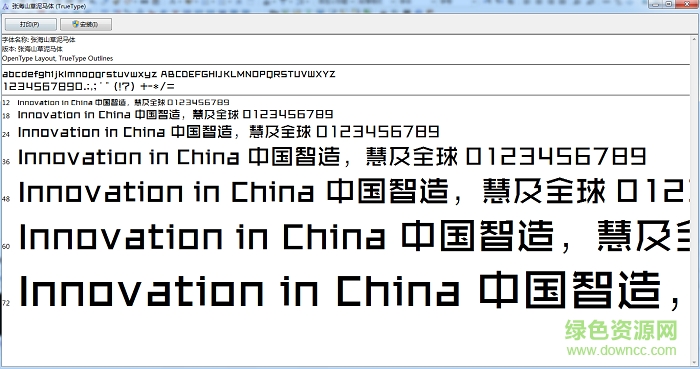
zhscnmt gbk1 0字體又叫張海山草泥馬體,這是一款又特色的中文廣告字體,字形簡潔干凈,方方正正,挺拔端正,辨識度高,喜歡的朋友快來下載吧!
體剛勁有力,完美無比,可應(yīng)用于卡通設(shè)計、繪畫藝術(shù)、產(chǎn)品創(chuàng)意、平面廣告、印刷包裝等領(lǐng)域!